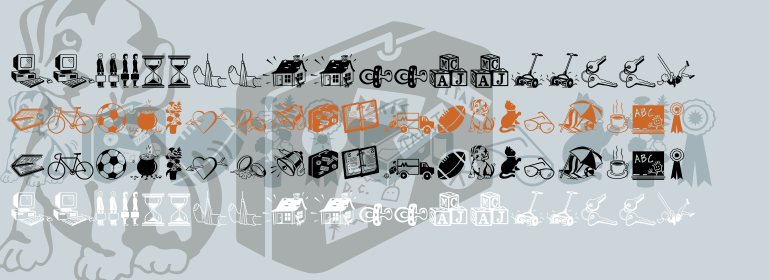
Milestones®
Milestones®,这款字体结构工整、笔画清晰,兼顾美观与易读性,适用于标题、正文、海报、包装、LOGO 等多种场景。字形优雅稳定,风格百搭耐看,适配日常排版与创意设计,让文字呈现更舒适、更具质感。Milestones®一笔一画,皆是细节,以均衡的比例、流畅的线条打造舒适视觉体验,字形端正大气,风格简约现代。无论是商业设计、品牌宣传还是日常排版,都能轻松驾驭,让文字更有格调与力量。Milestones®字体下载。
字体品牌: Monotype 设计师:Monotype Design Studio 字体分类:符号 字体属性:外文 字符集:Unicode 发布时间: 2018